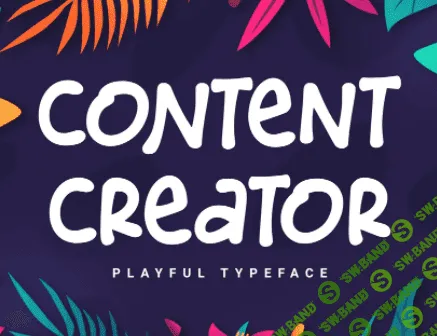
Название: Content Creator - Playful Typeface (2021)
Content Creator - Playful Typeface - это шрифт на тему комиксов, который можно использовать для ваших дизайнерских нужд. как следует из названия, этот шрифт предназначен специально для создателей контента, чтобы улучшить качество дизайнов и проектов, над которыми они работают.
Content Creator идеально подходит для дизайна, логотипов, социальных сетей, брендов, рекламы, дизайна продукта, рукописных цитат, упаковки продукта, заголовков, плакатов, товаров и другого дизайна.